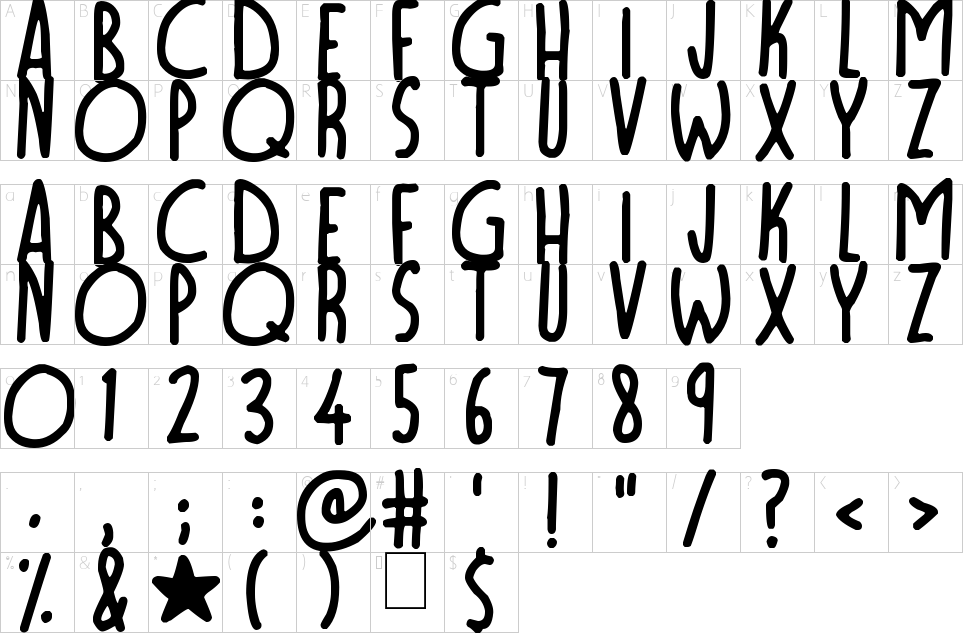
A fonte Moonlight é uma elegante escolha para aqueles que desejam um toque especial em seus designs digitais. Desenhada pelo incrível Darrell Flood, Moonlight oferece uma sensação de tranquilidade e serenidade, perfeitamente adaptada para qualquer projeto que deseje um tom de calma e luz. Seja para anúncios, logotipos ou design de web, Moonlight adquire um ar único que pode fazer a diferença. Com um design sofisticado e uma paleta de caracteres rica, esta fonte garante uma experiência visual única. Desenvolvida para atender a uma gama de necessidades de design, Moonlight é uma escolha impecável para qualquer projeto que deseje um toque de beleza e tranquilidade. A fonte Moonlight é uma ótima opção para quem está em busca de uma fonte gráfica gratuita, sem comprometer em qualidade.